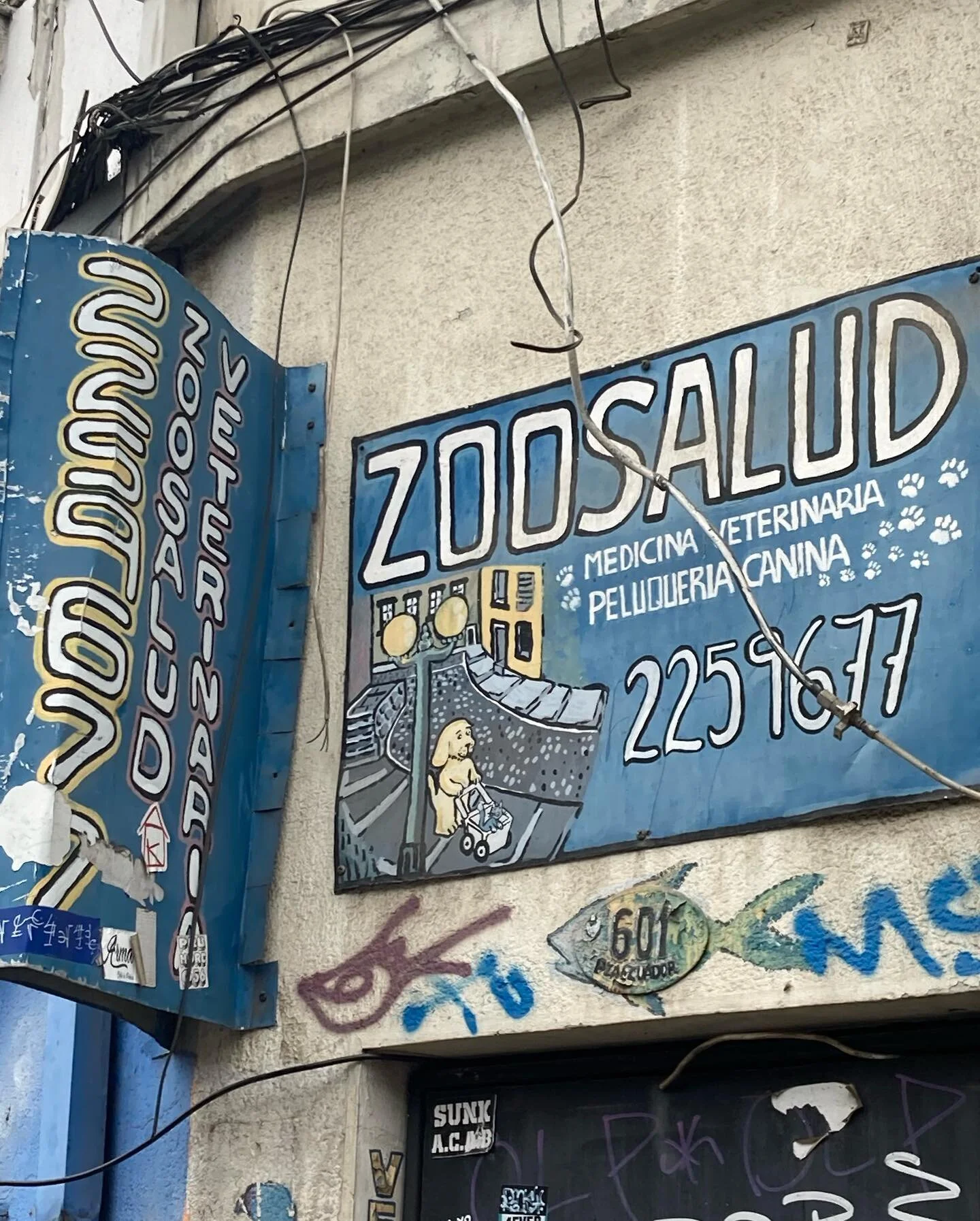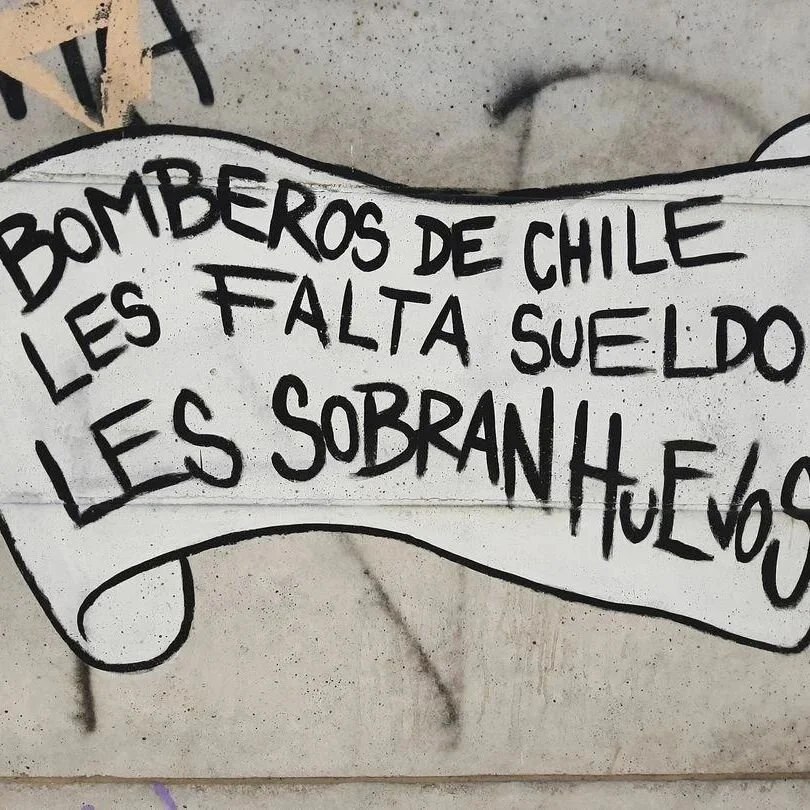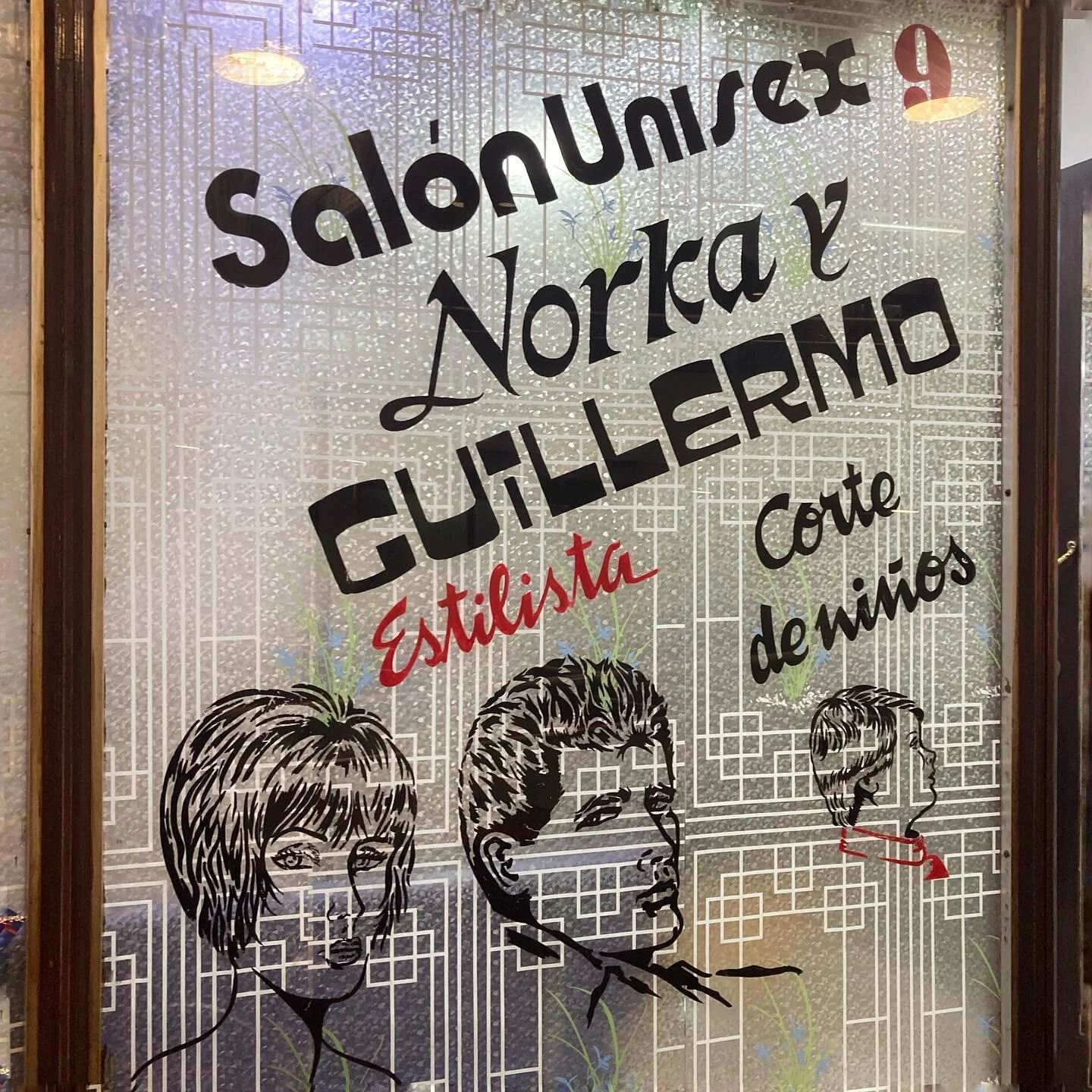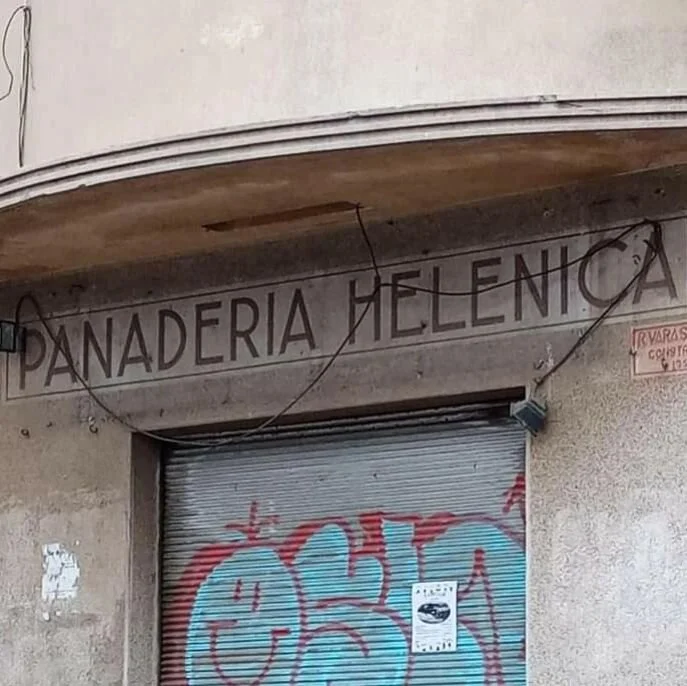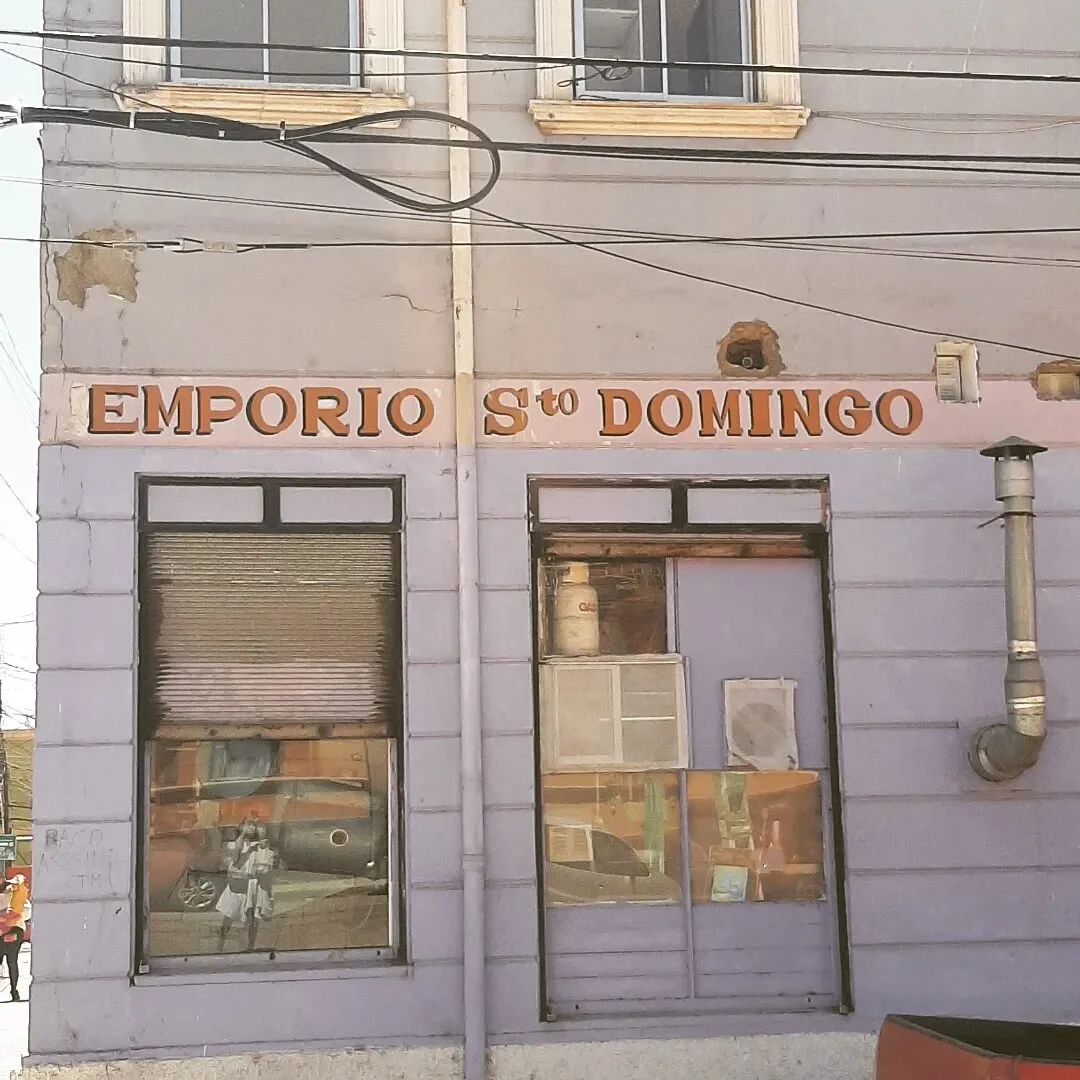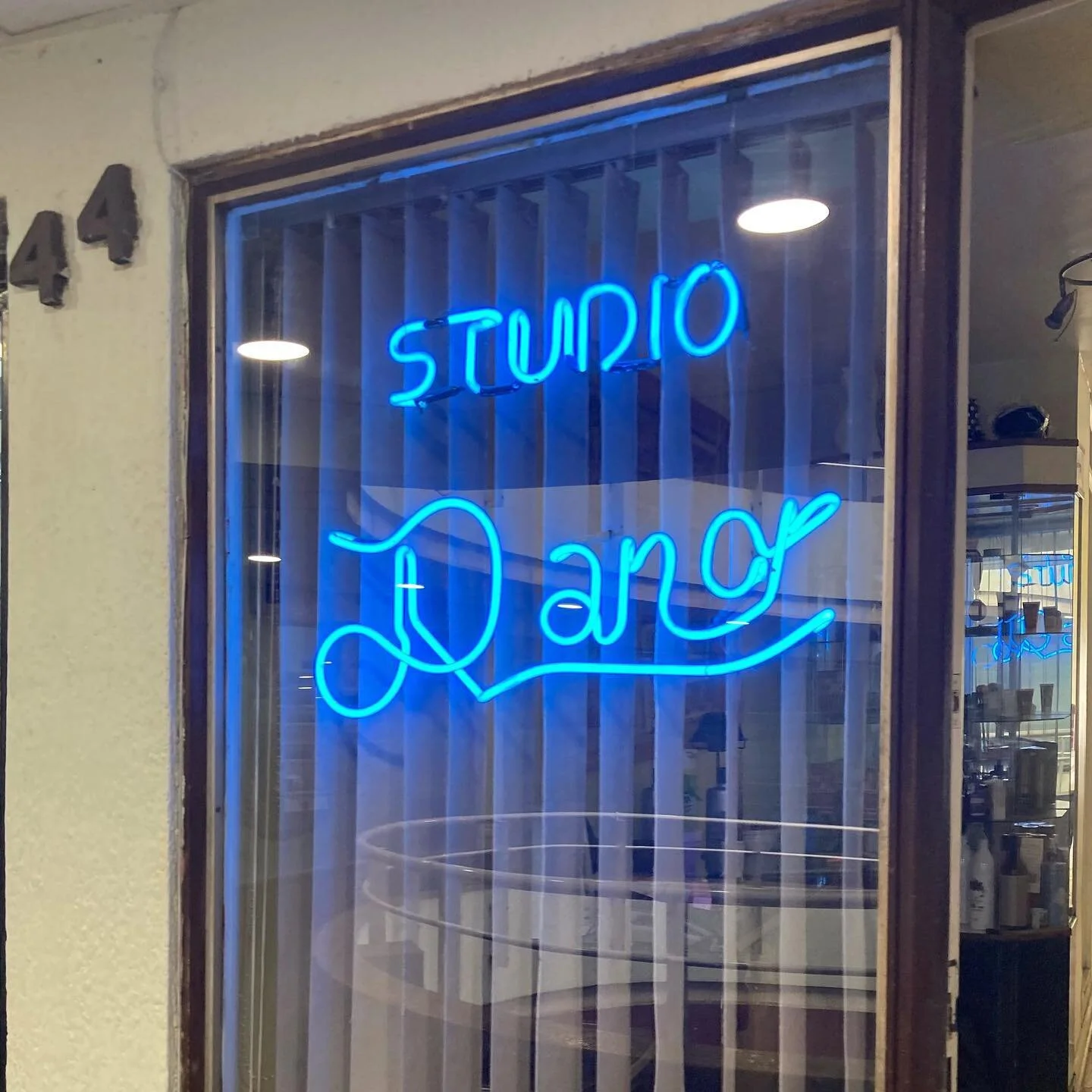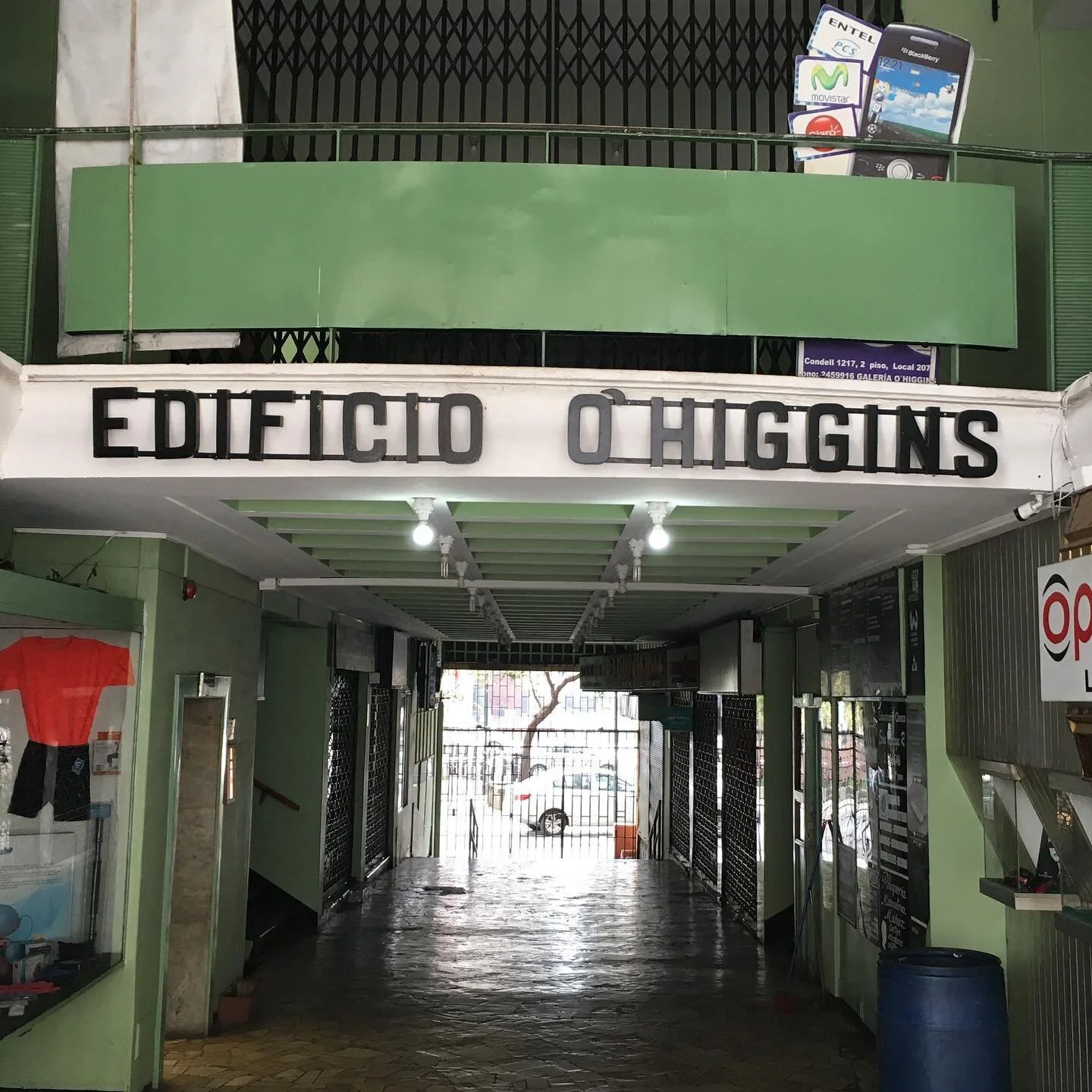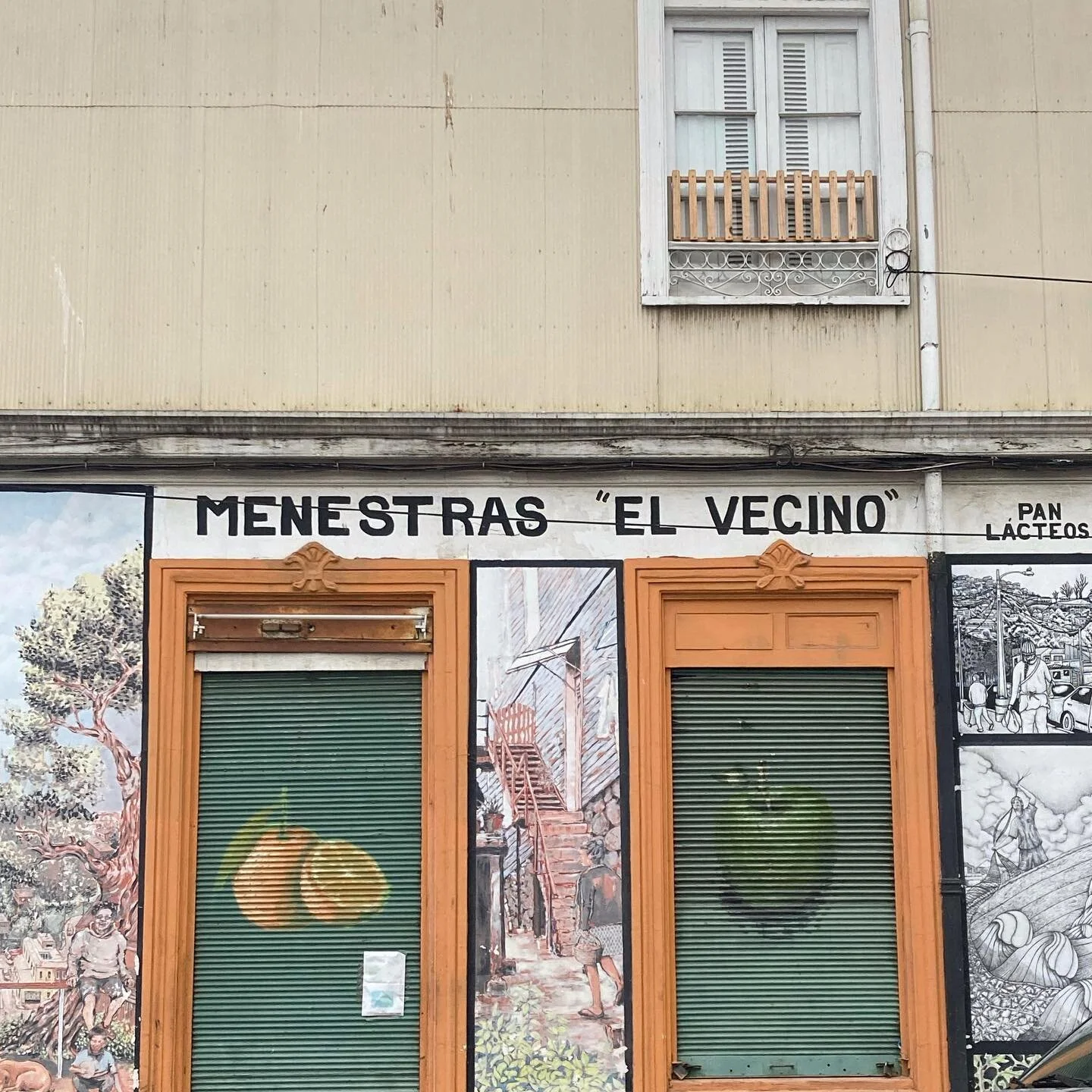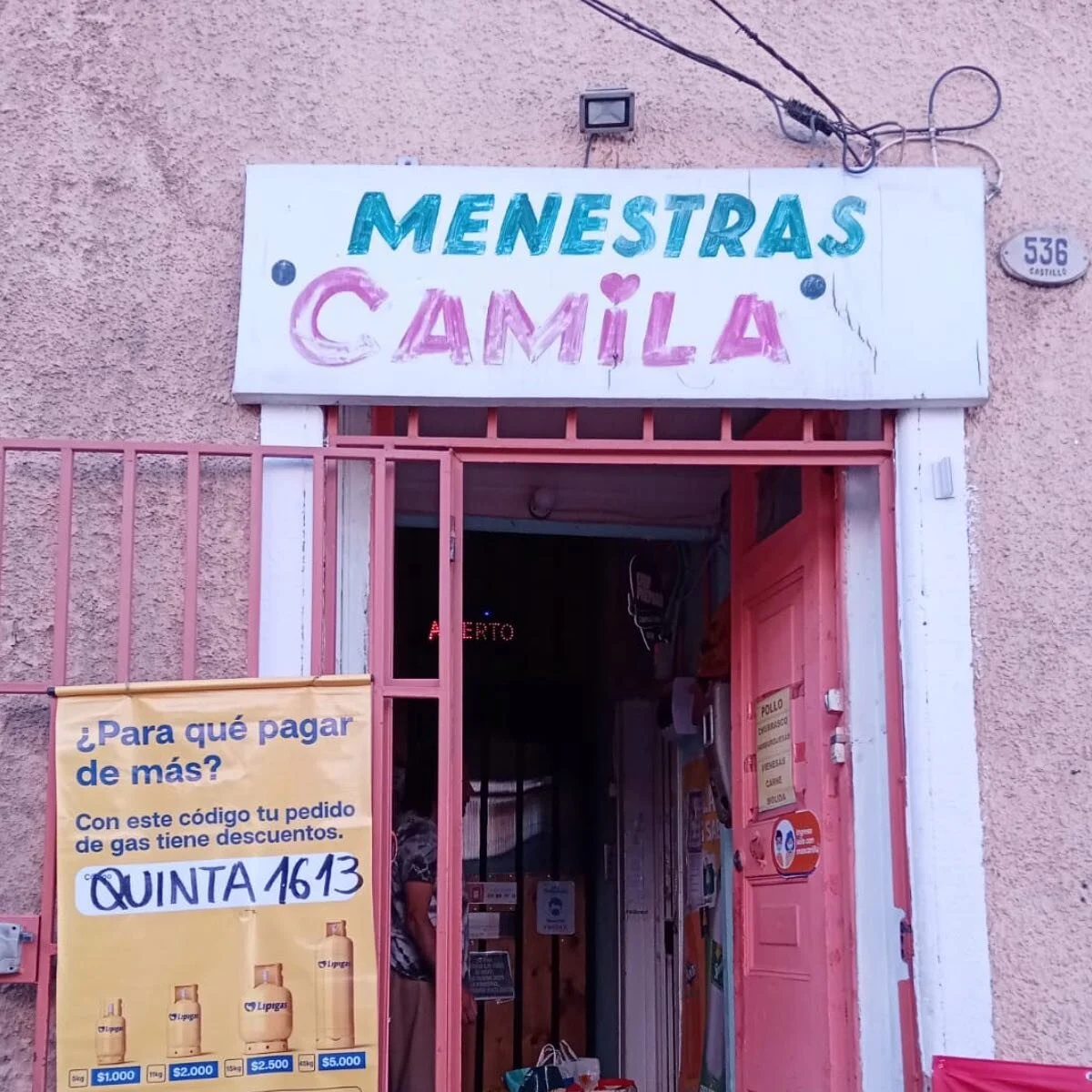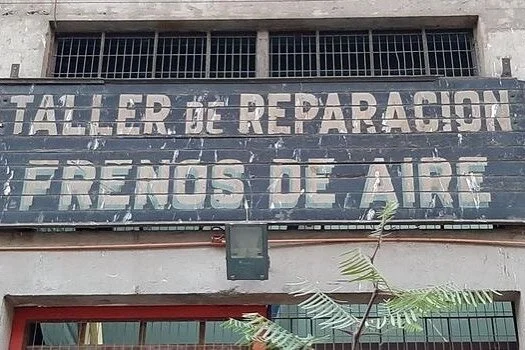
Abecedario Porteño
En cada letra una historia del puerto
Te invitamos a conocer Valparaíso a través de sus letras. Cada una de ellas tiene un doble significado; cuenta una historia del puerto, la de sus negocios, galerías o mercados, y también, forma parte de la cultura visual de esta original ciudad.
Descubrirás de la A a la Z, el abecedario completo del puerto, creado lúdicamente, con los carteles de lugares que todo porteño conoce, como el famoso bar Roma, icono del carrete universitario, frente a la Universidad de Playa Ancha, las ópticas Koch donde puedes encontrar un tesoro de los años setenta u ochenta o el amado Guria, con el mejor pan batido de Valpo.
Estos carteles también dan cuenta de la inagotable originalidad tipográfica de Valparaíso, que cambia en cada esquina y está basada en lo vernacular, a diferencia de ciudades modernizadas pobladas por cadenas y stripcenters. En el puerto cada uno hace su cartel y cada cartel es diferente al otro.
Este registro nace de la cuenta de Instagram TypoValpo, creada para recolectar las tipografías de la ciudad y compartirlas en Instagram. Poco después de su creación, la cuenta se convirtió en un espacio digital con vida propia, evidenciando el interés de la comunidad por el tema.
Los seguidores se convirtieron rápidamente en contribuidores, compartiendo con la cuenta las tipografías que veían en sus trayectos diarios. Por otra parte, se comenzaron a producir conversaciones en la sección de comentarios sobre ciertos lugares, negocios y muros de la ciudad.
Esta espontánea participación de la comunidad digital evidenció el patrimonio vivo que son las tipografías de una ciudad, las cuales evocan historias personales y colectivas, vivencias cotidianas de los habitantes quienes interactúan con estos carteles desde lo visual y desde el significado literal del lugar que anuncian.
Por eso, a través de esta exposición, te invitamos a poner en valor estos carteles, los locales y sus ofertas, reconociendo así su riqueza y lo extraordinaria que es la vida en Valparaíso. Empieza por la letra que quieras y explora esta ciudad única.
Nuestro proyecto ha crecido y se ha expandido a diferentes países de América y Europa. En este momento se encuentra formando parte de una muestra internacional de diseño de carteles en la Plaza Juan Goytisolo en Madrid, y que luego se trasladará a la Central de Diseño, en el Centro Cultural Matadero Madrid, durante el mes de diciembre.
El tema elegido para la convocatoria de Carteles de Madrid Gráfica en 2022 fue el de la ciudad recuperada como espacio para la vida y la oportunidad.
La propuesta para este año tenía como lema obligado «Ciudades abiertas», y podría estar escrito en cualquier idioma. Los carteles podían acompañar el lema y el texto con una imagen o grupo de imágenes que describan las ciudades como espacios abiertos y llenos de posibilidades.
Un cartel creado con nuestro abecedario porteño, donde además se invita a conocer Valparaíso a través de sus letras, fue el elegido por el jurado.